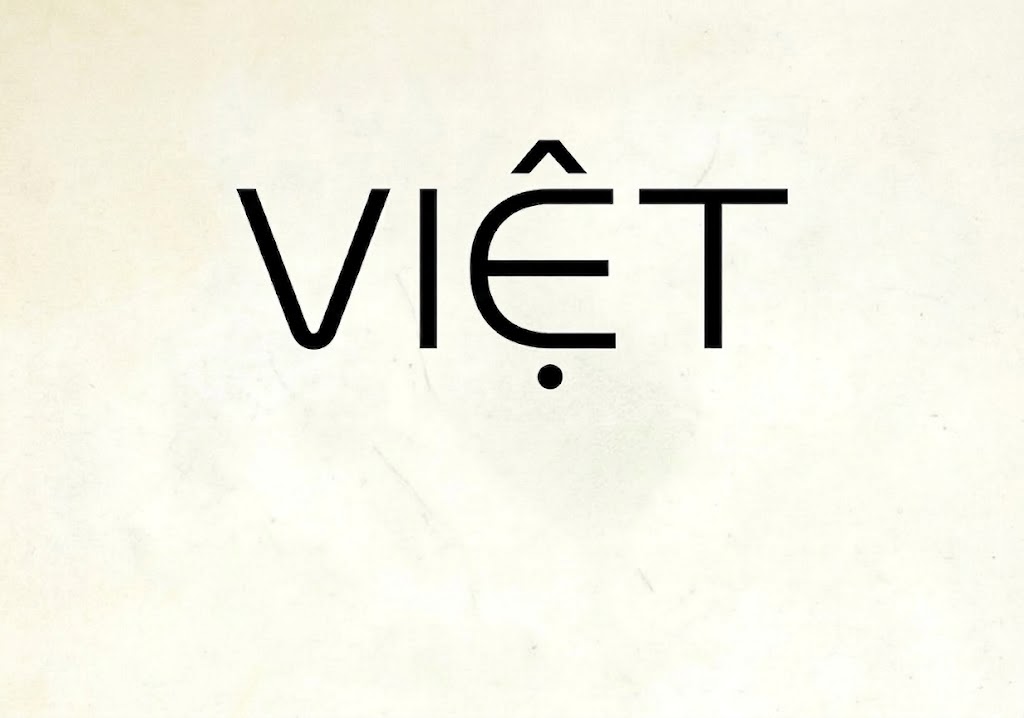
Font Việt hóa 1FTV Dune Rise
1FTV Dune Rise
Trong xu hướng sáng tạo nội dung số hiện nay, các phông chữ mang phong cách tương lai và khoa học viễn tưởng đang ngày càng được ưa chuộng.
Những kiểu chữ này mang lại cảm giác công nghệ cao, huyền bí và vô cùng chuyên nghiệp cho các sản phẩm truyền thông.
Nếu bạn đang tìm kiếm một bộ chữ độc lạ để làm tựa đề phim, thiết kế banner công nghệ hay làm video ngắn, thì font 1FTV Dune Rise chính là lựa chọn hoàn hảo.
Giới thiệu về font 1FTV Dune Rise
Font 1FTV Dune Rise là một phông chữ display không chân mang phong cách hiện đại, giả tưởng và đậm chất điện ảnh.
Bộ font này được tối ưu hóa ở phiên bản 001.000, mang lại cấu trúc hình học thanh thoát nhưng vô cùng sắc sảo.
Được chia sẻ rộng rãi bởi đội ngũ 1FTV, đây là giải pháp tối ưu cho những ai đang theo đuổi các dự án truyền thông mang concept vũ trụ hay tương lai tại Việt Nam.
Đặc điểm nổi bật của phong cách thiết kế Dune Rise
Sức hút khác biệt của font 1FTV Dune Rise đến từ cấu trúc chữ thanh mảnh kết hợp cùng các đường nét hình khối táo bạo.
Cảm hứng thiết kế của bộ font này mang đậm dấu ấn của các bộ phim giả tưởng thế hệ mới, nơi sự tối giản và tính công nghệ được đặt lên hàng đầu.
Điểm bứt phá lớn nhất nằm ở các ký tự đặc biệt như chữ O với một dấu chấm độc đáo ở chính giữa, hay các đường cắt ngang tinh tế của chữ A và H.
Phông chữ được xây dựng hoàn toàn theo cấu trúc all-caps (viết hoa toàn bộ), giúp tạo ra sự đồng đều tuyệt đối về mặt cao độ khi bạn sắp xếp các dòng tiêu đề cạnh nhau.
Để phông chữ vận hành mượt mà trên hệ thống máy tính và các phần mềm edit hiện nay, phiên bản font 1FTV Dune Rise đã được xử lý kỹ lưỡng về mặt kỹ thuật số.
Hệ thống khoảng cách chữ (kerning) và độ giãn dòng (tracking) đã được căn chỉnh chuẩn xác, giúp các ký tự luôn giữ được khoảng hở thẩm mỹ khi đứng cạnh nhau.
Bên cạnh hệ thống chữ cái viết hoa đồng bộ, phông chữ còn tích hợp đầy đủ dãy số từ 0-9 cùng hệ thống các ký tự đặc biệt, dấu câu thông dụng (.,;: ' " (!?) +-*/=).
Tiện ích này giúp bạn thoải mái sáng tạo nội dung đa dạng mà không lo bị lỗi hiển thị hay thiếu ký tự trong quá trình gõ.
Hình ảnh demo thực tế của font 1FTV Dune Rise
Để giúp bạn dễ dàng hình dung khả năng co giãn và hiển thị linh hoạt của phông chữ này trên các kích thước khác nhau, hãy cùng xem qua bảng mô phỏng thực tế:
• Kích thước nhỏ (12pt – 24pt): Các nét chữ thanh mảnh và khoảng cách mở rộng vẫn giữ được sự rõ ràng, dễ đọc trên màn hình điện thoại di động.
• Kích thước lớn (36pt – 72pt): Đây là không gian lý tưởng để font chữ phô diễn sức mạnh hình khối không gian, tạo hiệu ứng thị giác bay bổng cho các tiêu đề chính.
Ứng dụng của font Dune Rise trong thiết kế đồ họa và làm video
Sở hữu nét cá tính bứt phá và mang đậm chất tương lai, font 1FTV Dune Rise mở ra không gian ứng dụng rộng lớn cho các dự án marketing và truyền thông:
• Thiết kế thumbnail Youtube và ảnh thu nhỏ mạng xã hội: Đây là vũ khí tuyệt vời cho các chủ đề về công nghệ, vũ trụ, review đồ điện tử hoặc khoa học viễn tưởng để thu hút người xem bấm vào.
• Làm tiêu đề video ngắn (Tiktok, Shorts, Reels): Cấu trúc chữ độc lạ này giúp các câu từ khóa chính, tiêu đề mở đầu video trở nên vô cùng nghệ thuật và giữ chân người xem lướt chậm lại.
• Banner và poster phim giả tưởng: Hoàn hảo cho các poster giới thiệu sản phẩm công nghệ cao, banner trò chơi điện tử phong cách không gian hoặc bìa album nhạc cá tính.
• Nhận diện thương hiệu phong cách tối giản: Phù hợp làm logo dạng chữ khối cho các thương hiệu thời trang hiện đại, studio sáng tạo hoặc các công ty khởi nghiệp về công nghệ.